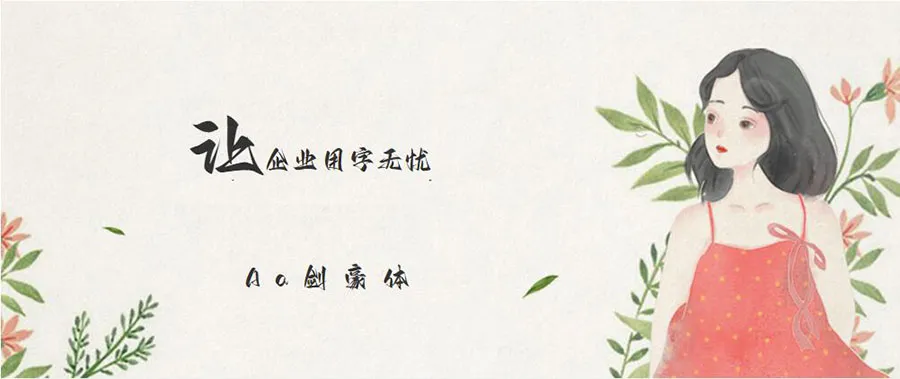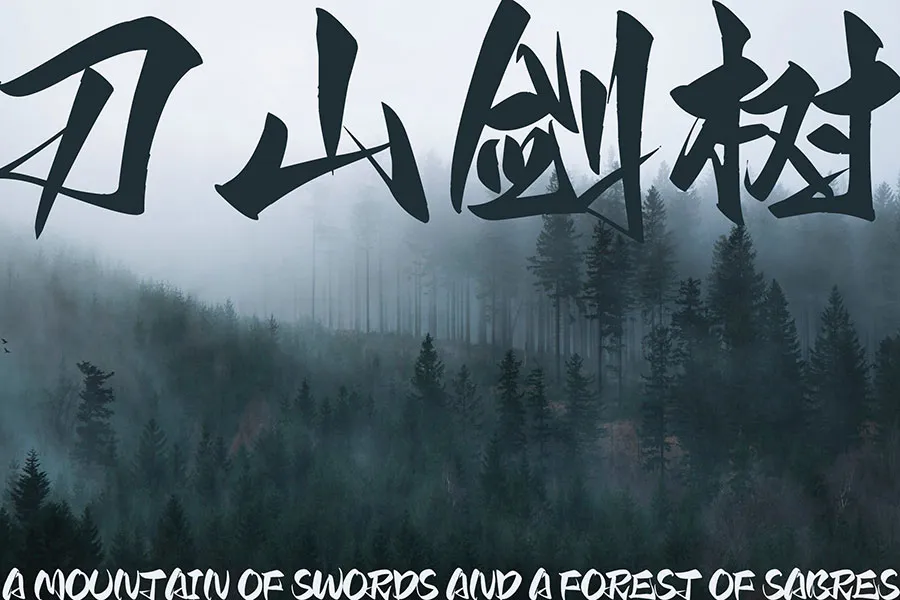
Aa劍豪體,是Aa字庫發佈的首款免費商用字體,充滿灑脫、豪放、江湖豪氣,個性十足,一筆一劃鋒芒畢露,比其他書法字體更加醒目,極具張力。筆畫末端的鉤刺極具特色,運筆飄忽快捷,筆跡瘦勁,轉折處可明顯見到藏鋒,露鋒等運轉提頓痕跡,是一種風格相當獨特的書法字體,非常適合應用於適合應用於藝術設計、平面設計、書法字帖等場景。